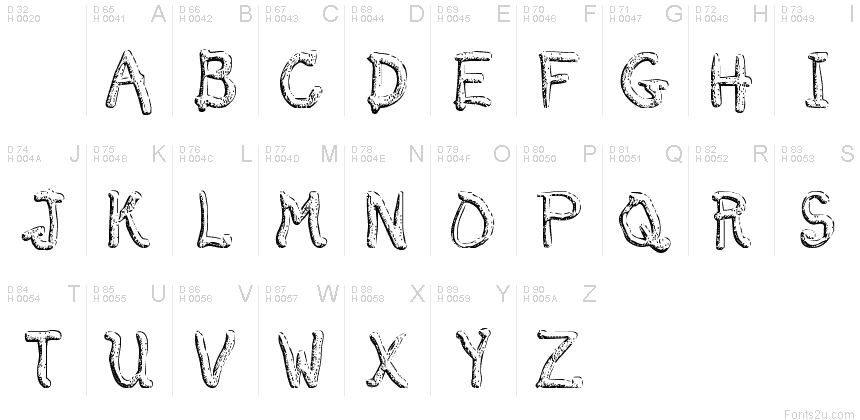
Smelted, bezplatné cartoon display písmo od S. Rolanda Frantze z deFaced fonts, sází na lepkavý, žárem pokroucený vzhled s uvolněným postojem, který známe z netradičních písem konce 90. let. Písmena působí měkce a napůl roztekle, s hrbolatými křivkami, zářezy připomínajícími kapky a roztroušenými výřezy, díky nimž písmo vypadá jako postříkané, slizké nebo čerstvě roztavené.
Hodí se na plakáty, herní tituly, party letáky, komiksové nadpisy a strašidelné obaly, kde je potřeba hravý nepořádek místo čisté geometrie. Použijte ho pro krátké titulky, úvodní karty, skici log nebo velké iniciály, kde tyto děravé, prověšené tvary dodávají i pár písmenům osobitý, lepkavý nádech.